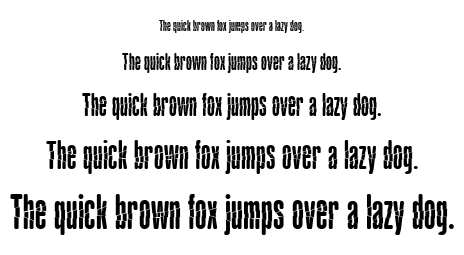
Esta tipografía es un experimento de rajado y mutilación sobre mi anterior tipografía grotesca Yacarena Ultra Sans. Este ejercicio de corte aporta a la fuente una temporalidad estilística (moda) de la que no se sabe hasta cuando perdurará en el diseño gráfico, mientras tanto aprovéchala en composiciones de diseño de carteles, publicidad o para titulares en diseño editorial.
This typeface is an experiment in cracked and grotesque mutilation of my previous Yacarena Ultra Sans typeface. This exercise gives cutting power temporality stylistic (mode) of which is not known until they endure in graphic design, meanwhile kicking butt in compositions poster design, advertising or editorial design headlines.